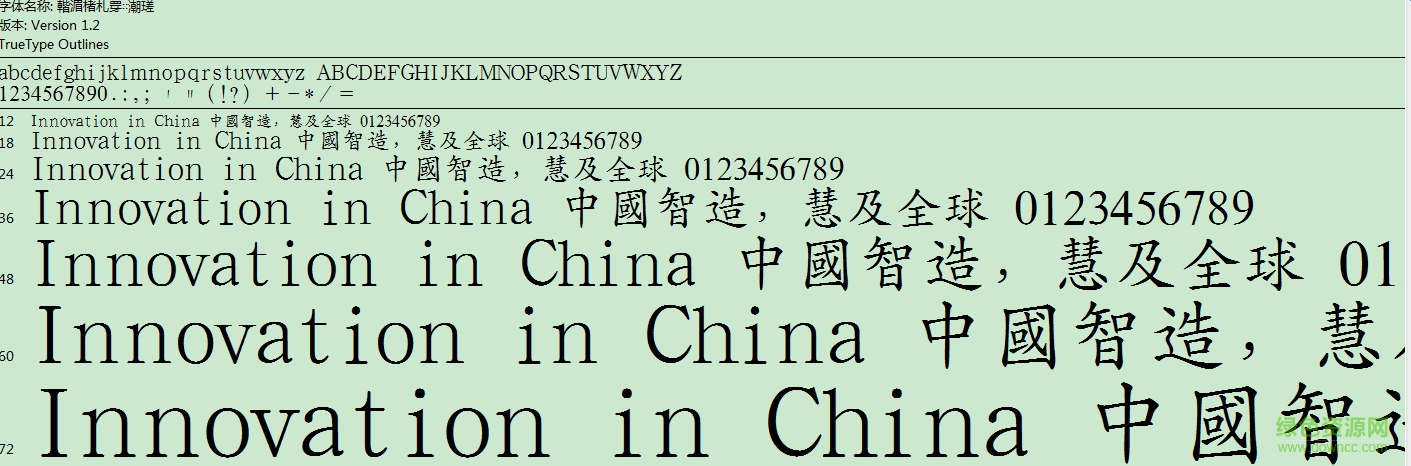
漢鼎繁中楷字體是一款漢鼎字體,可以用于廣告設(shè)計(jì)、海報(bào)設(shè)計(jì)等方面。美工朋友們不要錯(cuò)過喲,能更加具有光彩性。還能充分發(fā)揮字體的靈動(dòng)感,快來綠色資源網(wǎng)免費(fèi)下載吧。
提供了中英文雙語字體,中文為繁體??w形體方正,筆畫平直,可適用于廣告設(shè)計(jì)、平面設(shè)計(jì)、印刷包裝、報(bào)紙雜志等行業(yè)。